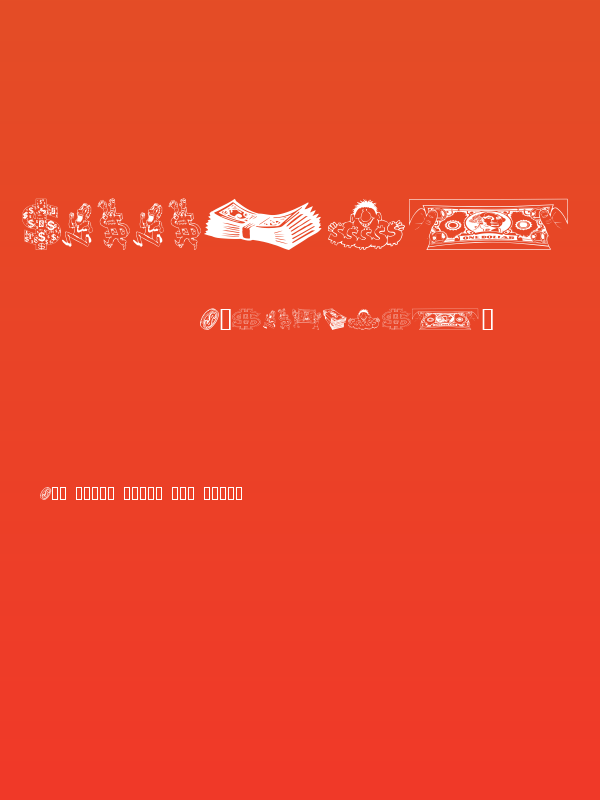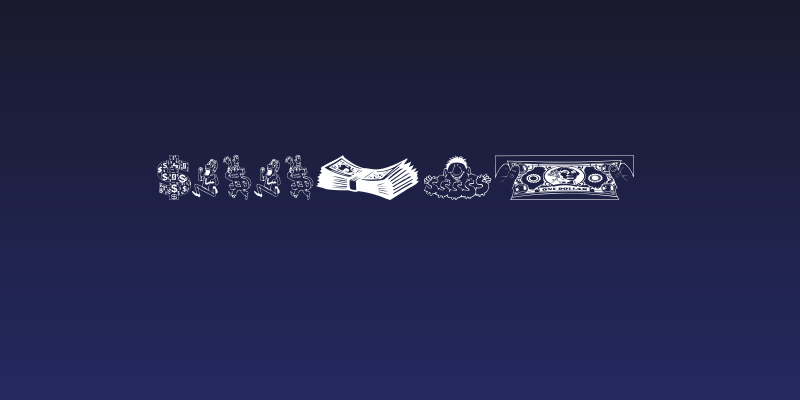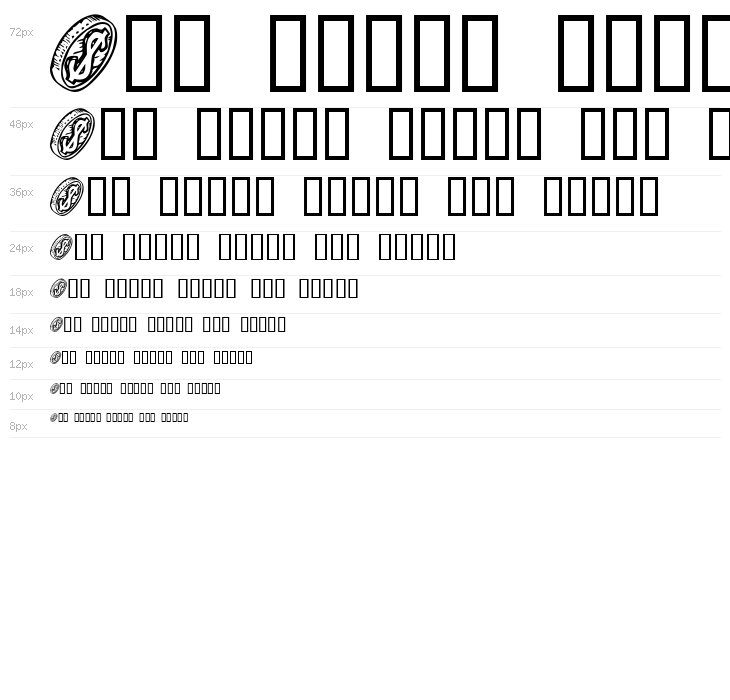
Moolah Font
✎ Dingbats
| Caso de uso | Logos, Posters, Novelty items |
| Proyectos propuestos | Ideal for financial-themed posters, playful advertisements, children's educational materials about money, and novelty designs. |